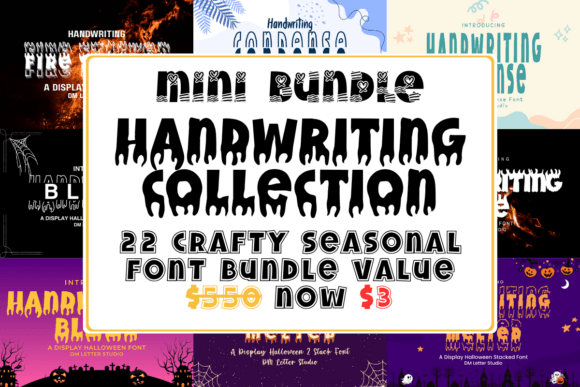
Handwriting Collection Font Bundle
Jika Anda mencari aset berkualitas tinggi seperti Handwriting Collection Font Bundle, paket premium ini adalah pilihan fantastis untuk proyek kreatif Anda.
Baik Anda membuat produk POD (Print on Demand), undangan pernikahan, atau grafis media sosial, Handwriting Collection Font Bundle adalah pilihan yang sangat ideal.